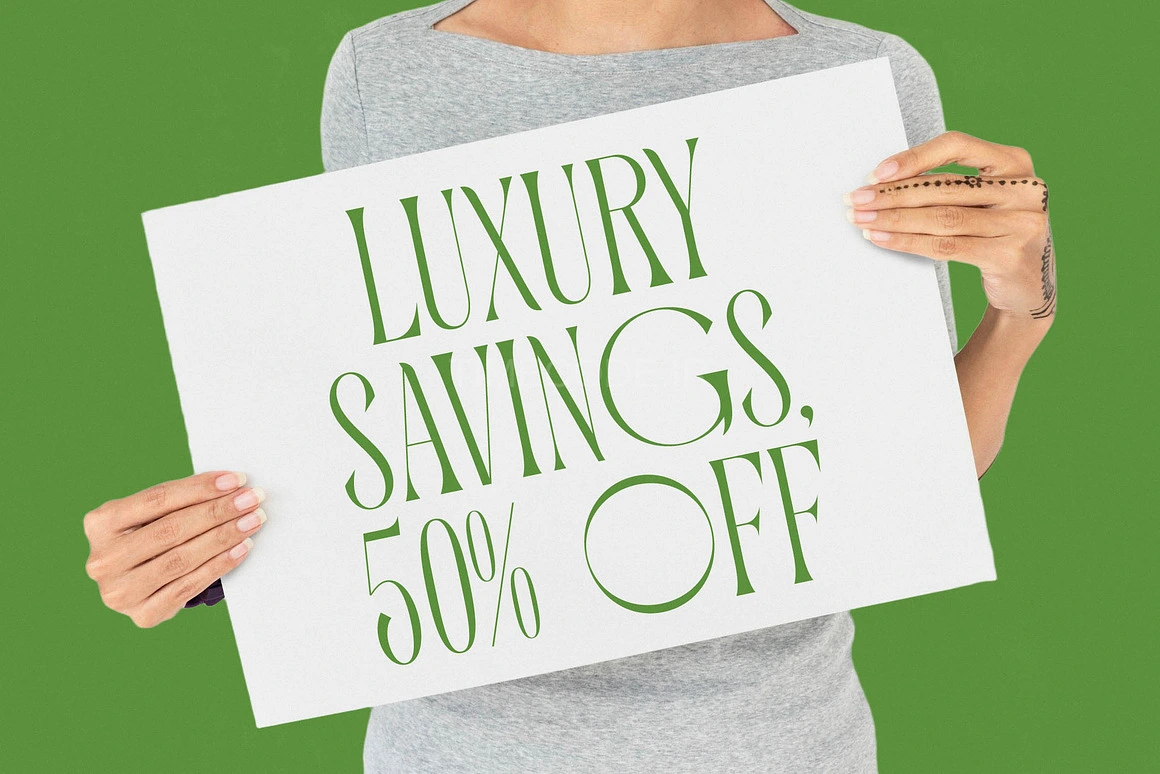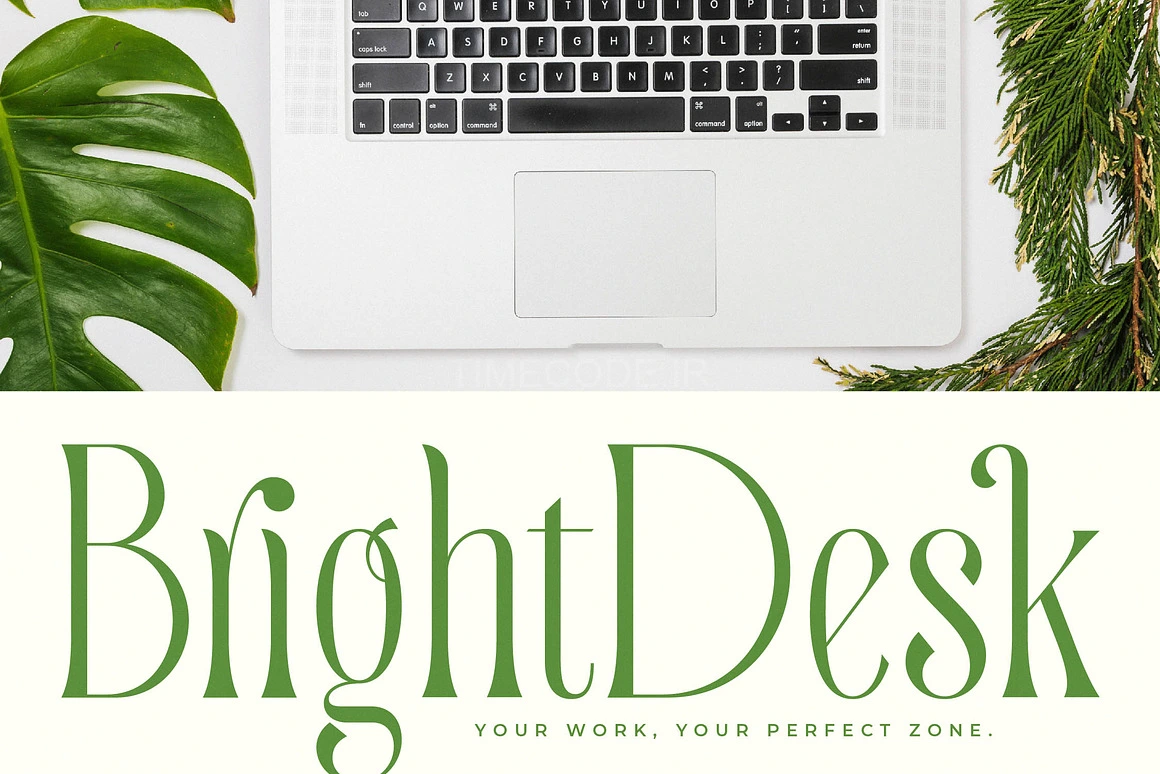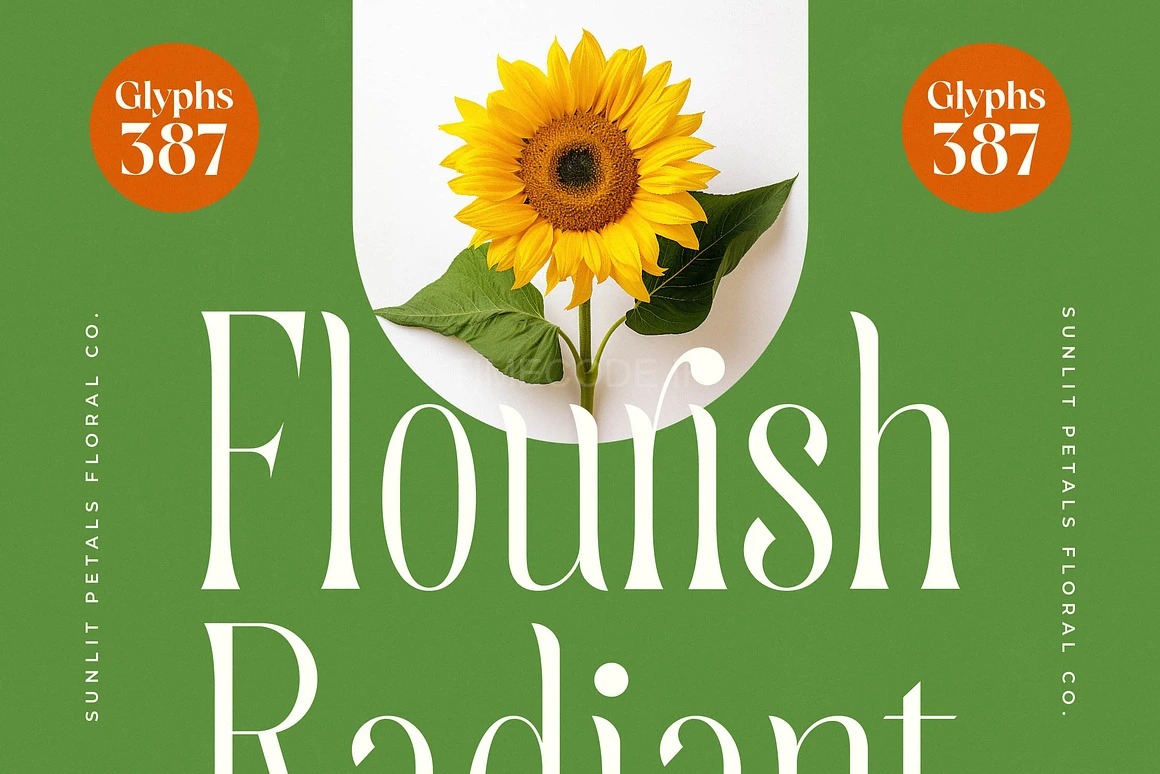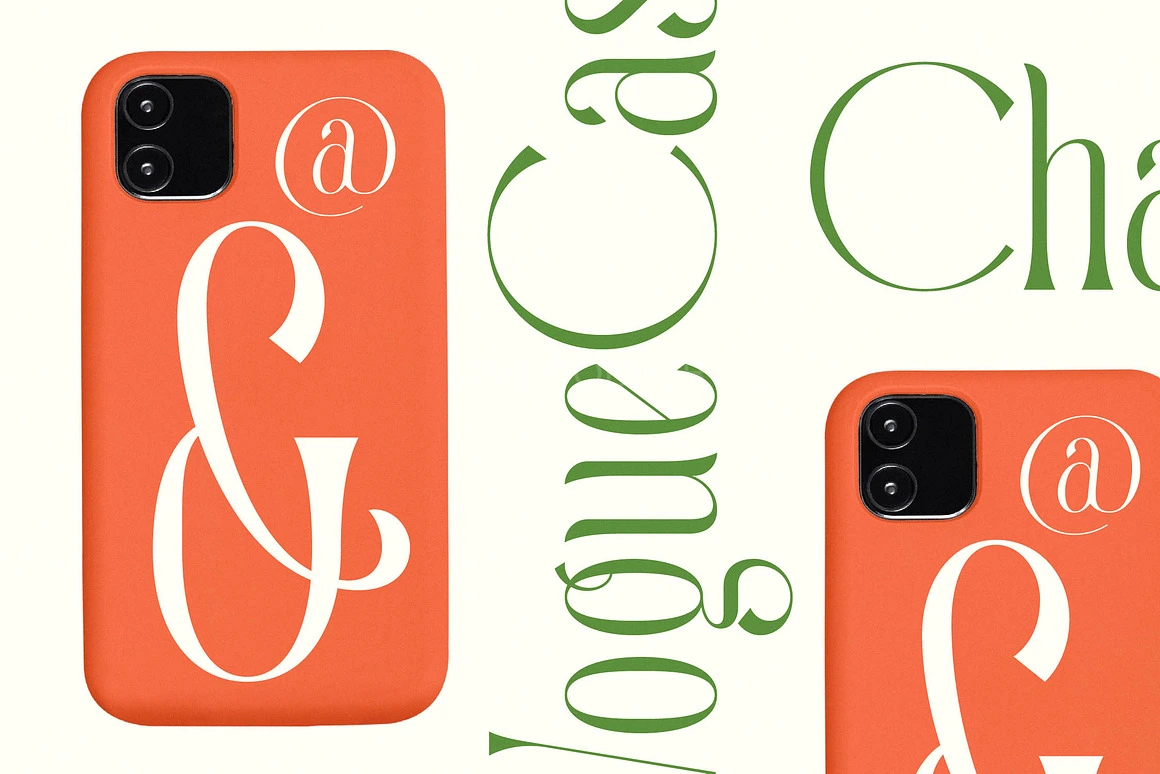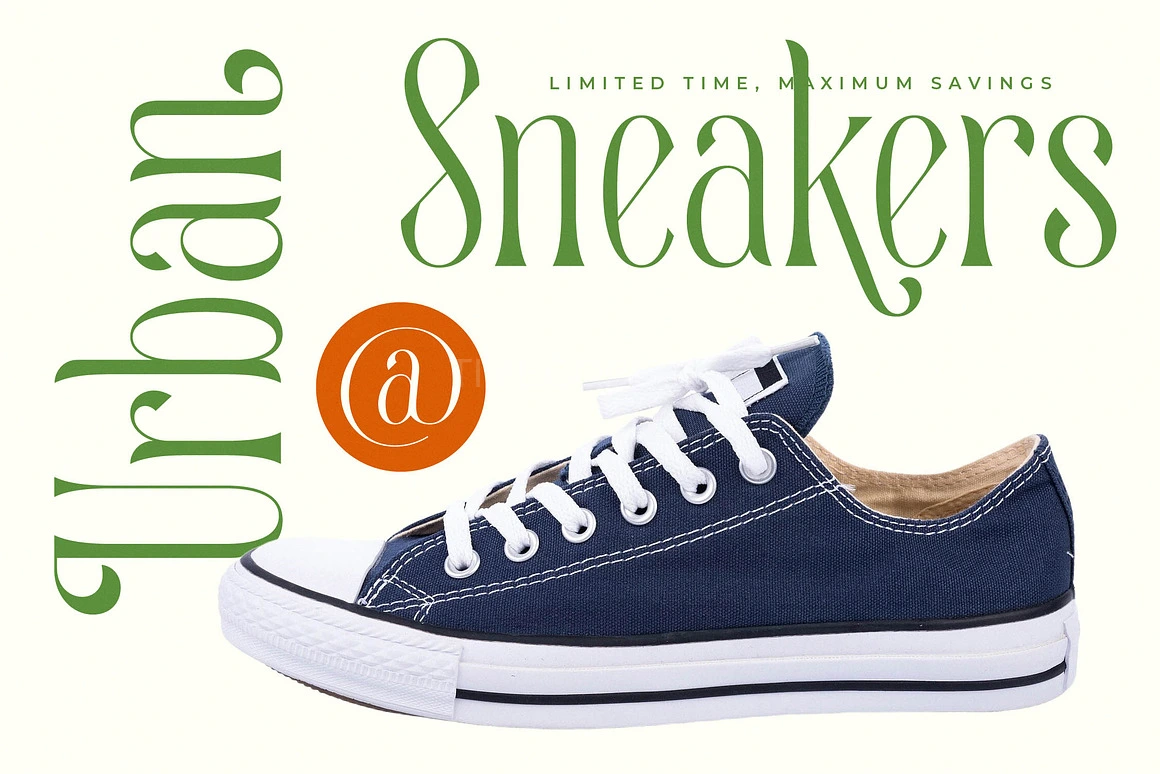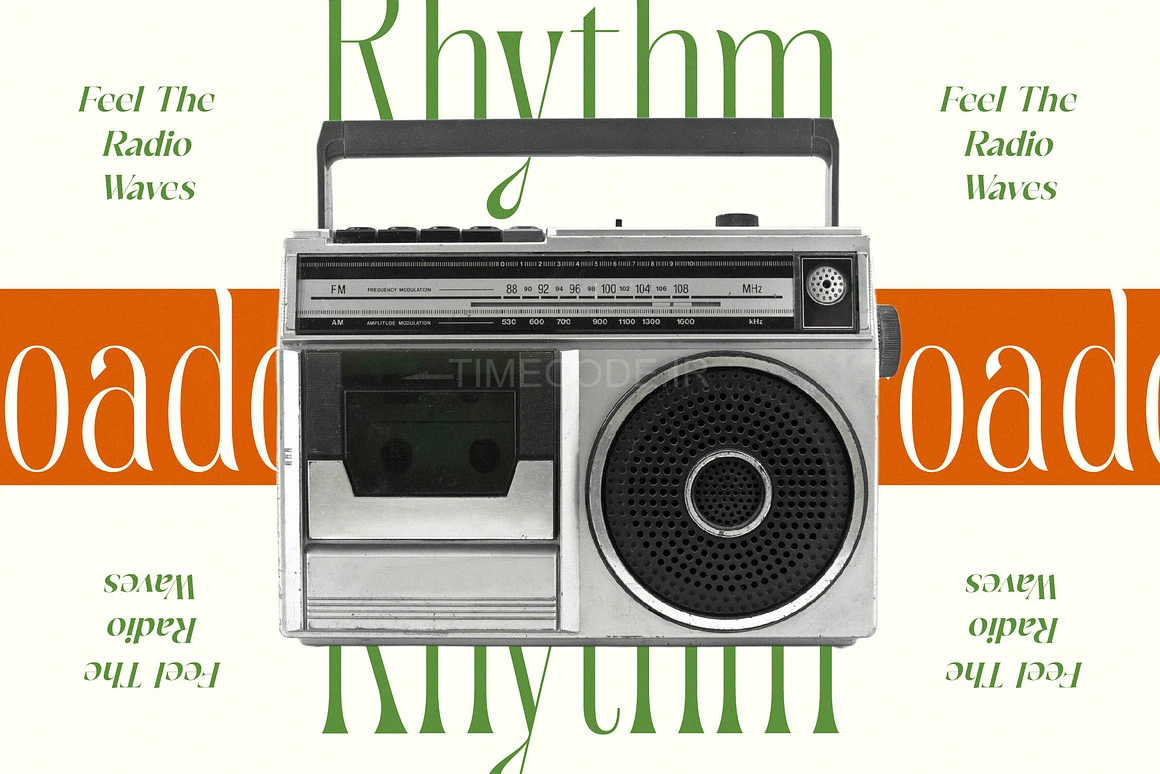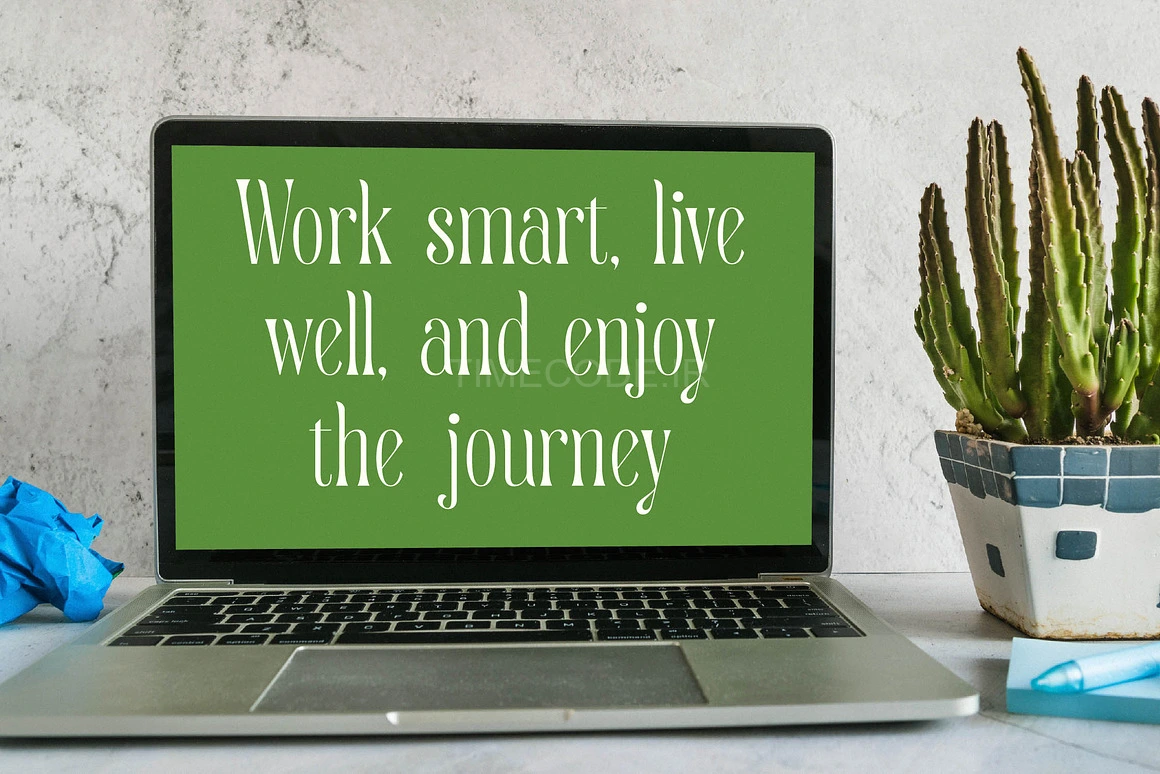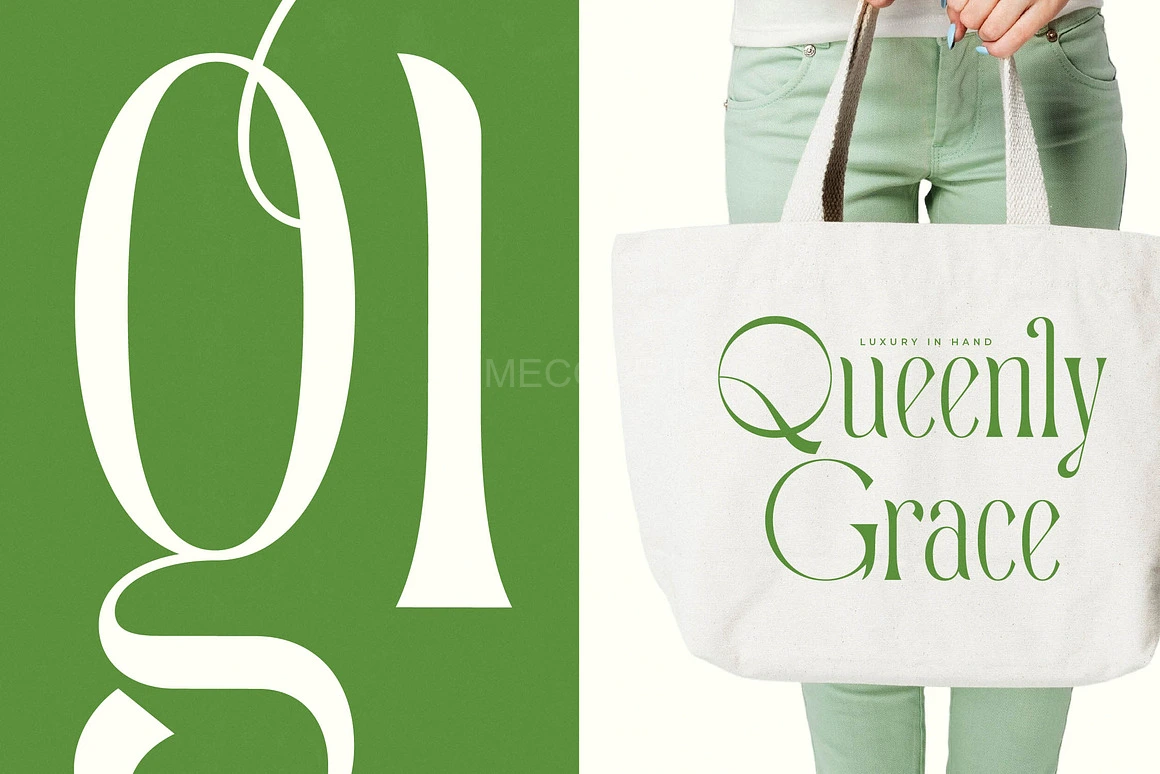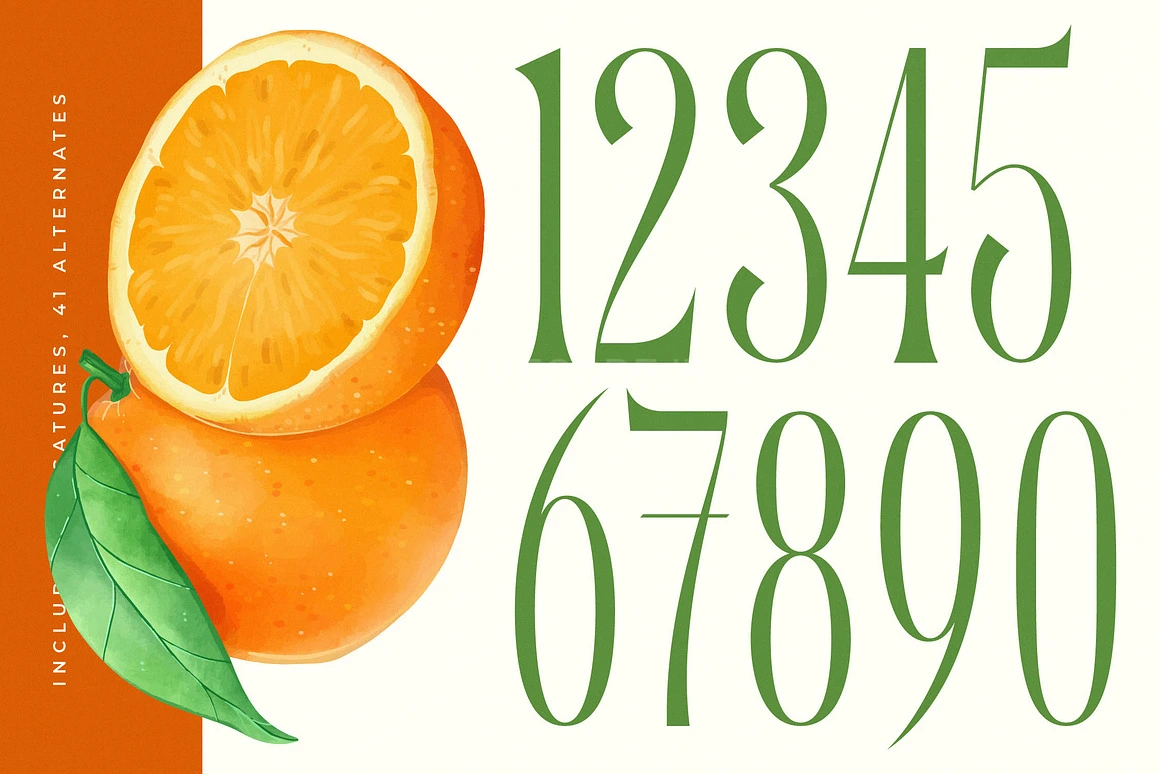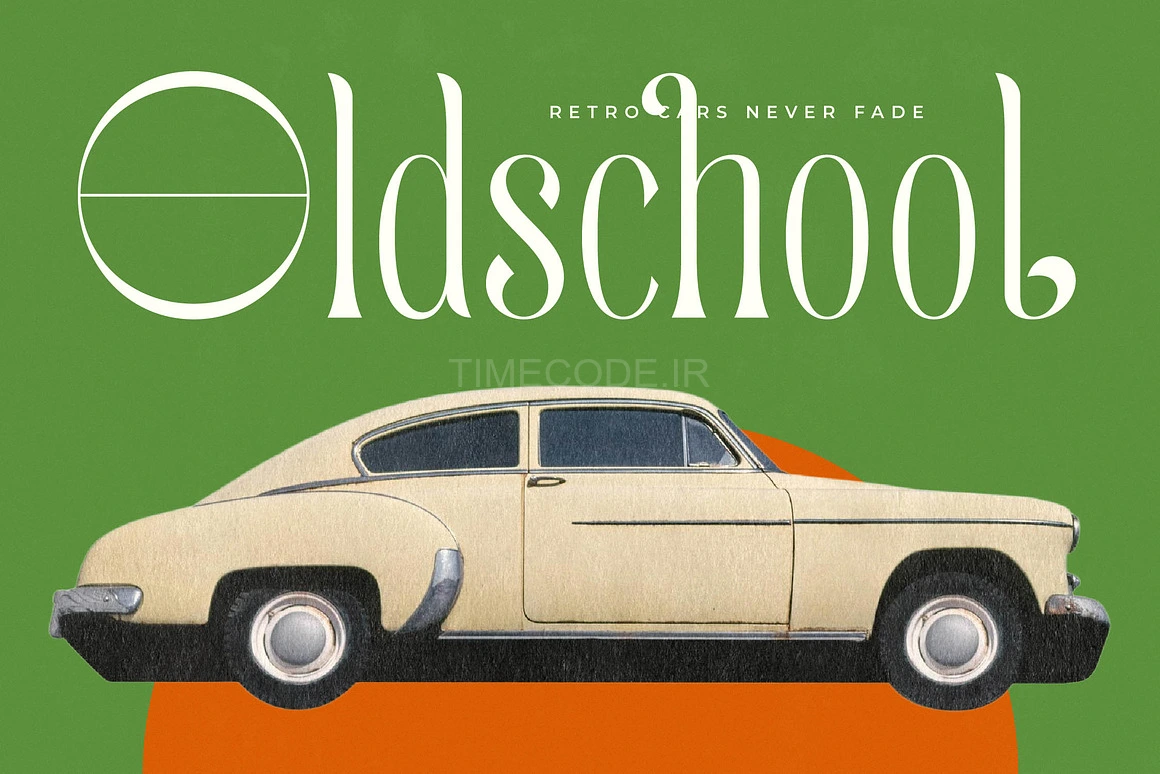
• Quiselle Modern Serif Font
فونت انگلیسی سریف فانتزی
Quiselle یک فونت سریف مدرن، مناسب برای هر پروژه‌ای از قبیل: لوگو، پروژه‌های برندینگ، طراحی لوازم خانگی، بسته‌بندی محصول، ماگ، نقل قول، پوستر، ساک خرید، تی‌شرت، جلد کتاب، کارت ویزیت، کارت دعوت، کارت تبریک، لیبل، عکاسی، واترمارک، رویدادهای ویژه، و تمام پروژه‌های لوکس و زیبای دیگری که به حس و حال یک فونت سریف لوکس نیاز دارند.
• 16 لیگچر (حروف ترکیبی) و 41 کاراکتر جایگزین
• حروف بزرگ و کوچک
• اعداد
• علائم نگارشی (استاندارد OpenType)
• اکسان‌ها (کاراکترهای چندزبانه)
• لیگچرها و مجموعه استایل‌های جایگزین (Stylistic Set)
Quiselle - Modern Serif Font , from Timelesstype.Co , Suitable for any projects such as: logos, branding projects, homeware designs, product packaging, mugs, quotes, posters, shopping bags, t-shirts, book covers, name card, invitation cards, greeting cards, label, photography, watermark, special events, and all your other luxury and beautiful projects that need a Luxury Serif taste.
- Ligature 16 Alternate 41
- Uppercase and Lowercase
- Numerals
- Punctuations (OpenType Standard)
- Accents (Multilingual Characters)
- Ligatures and Alternative Style Stylistic Set